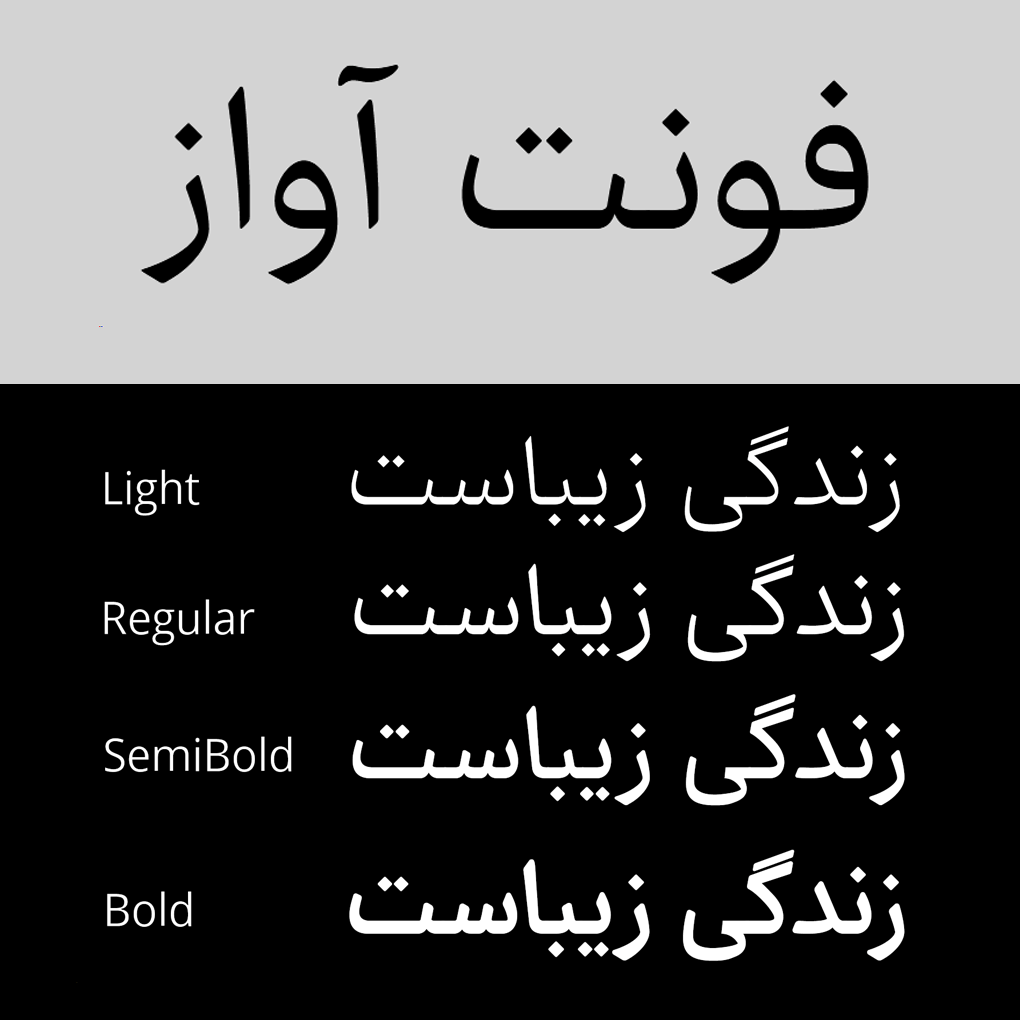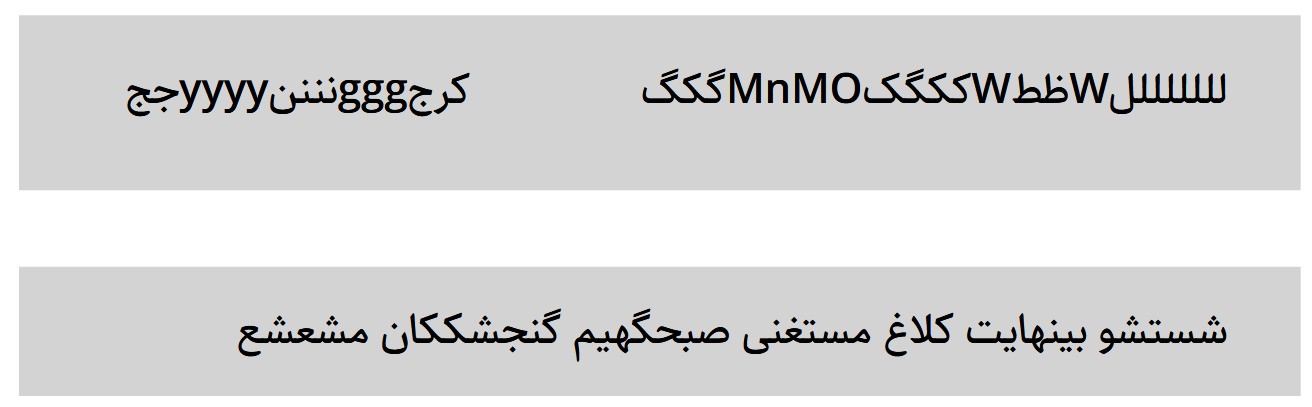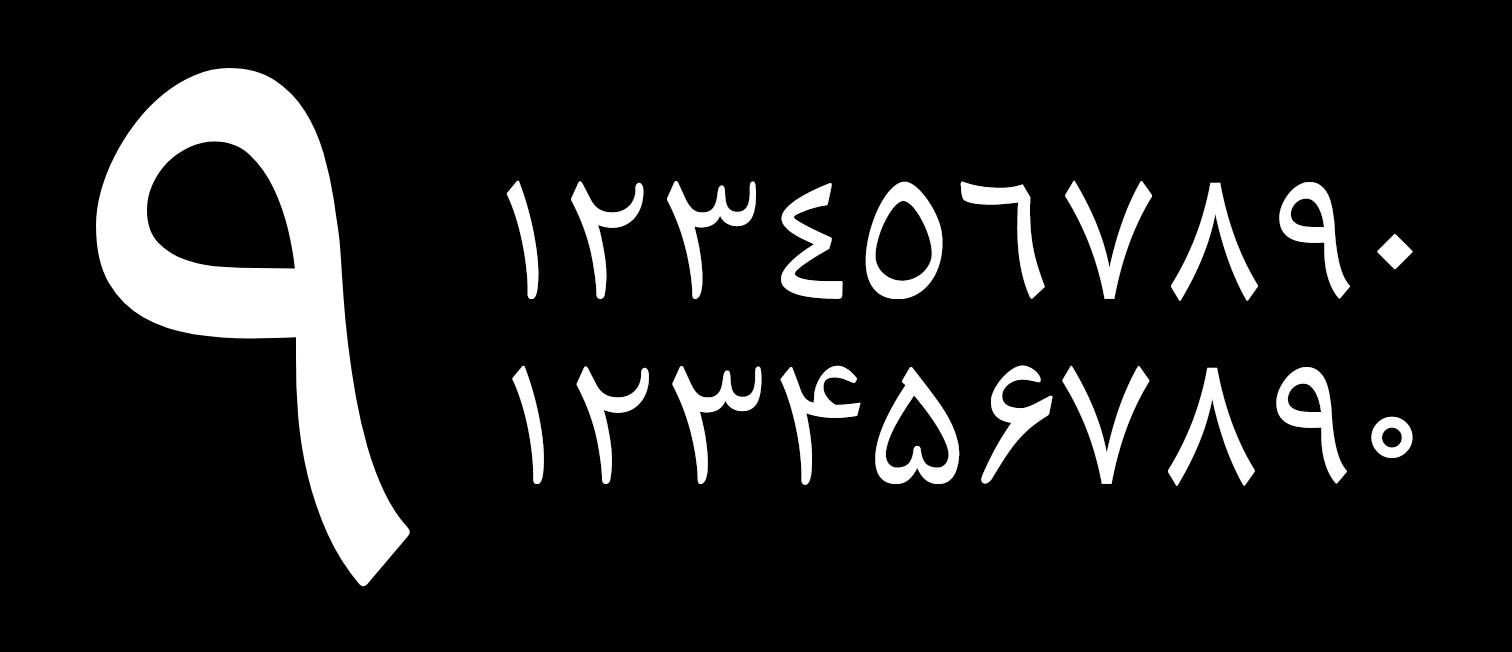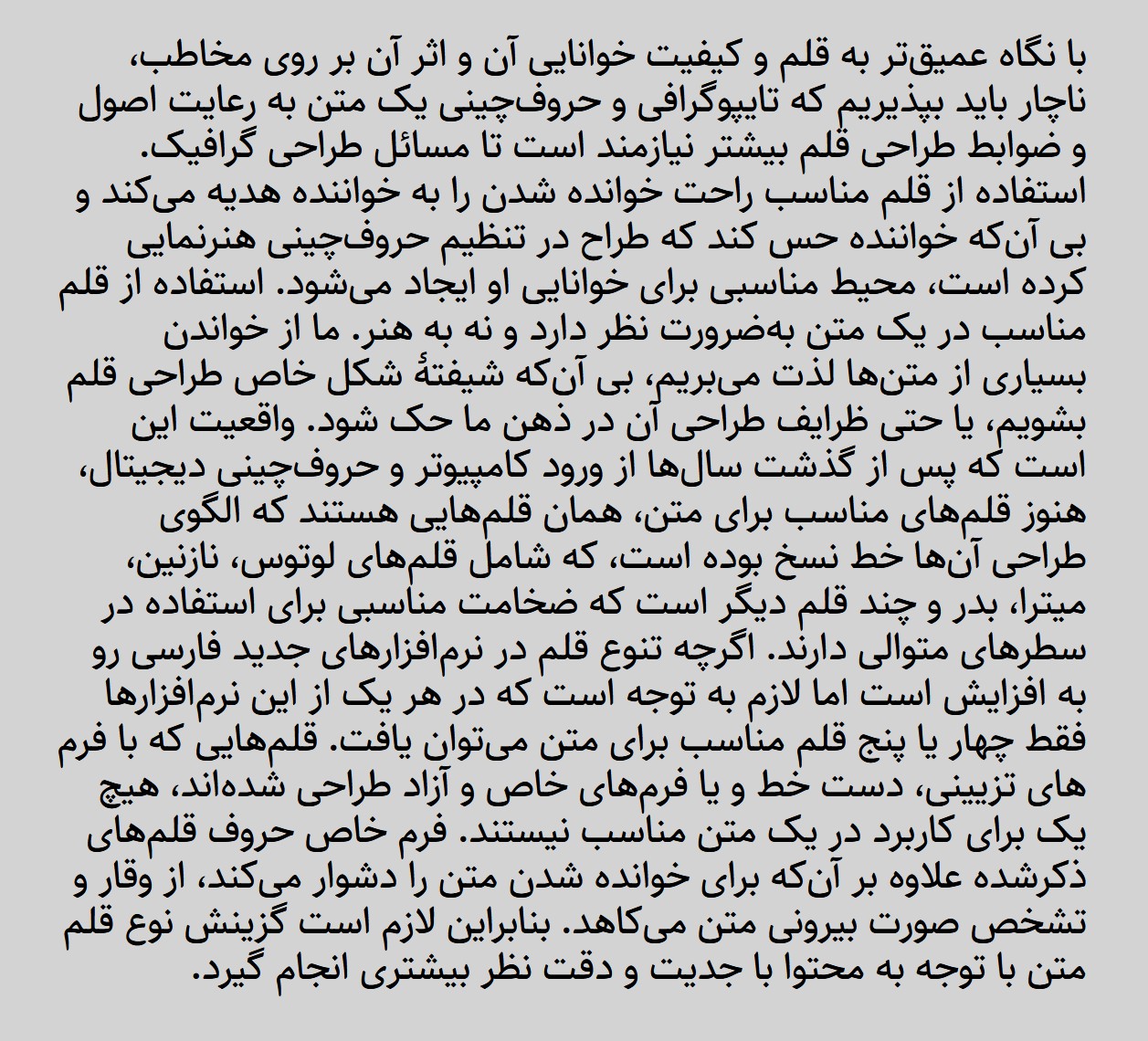
فونت آواز؛ نسل جدید فونت نسخ برای طراحان حرفه‌ای
اگر شما هم سال‌ها با فونت‌هایی مثل زر یا نازنین کار کرده باشید، احتمالاً با مشکلاتی مثل کرنینگ ضعیف، فاصله‌گذاری نامناسب بین حروف و محدودیت در استفاده در محیط وب روبه‌رو شده‌اید. این فونت‌ها اگرچه ریشه در طراحی فارسی دارند، اما دیگر پاسخگوی نیازهای امروز طراحان نیستند.
اینجا بود که فونت آواز به‌عنوان یک فونت فارسی مدرن بر پایه‌ی خط نسخ طراحی شد. فونتی که نه‌تنها اصالت خوشنویسی را حفظ کرده، بلکه تمام ایرادات نسل قبل را برطرف کرده و با استانداردهای جهانی طراحی فونت هماهنگ است.
ویژگی‌های کلیدی فونت آواز
فونت آواز دقیقاً برای کسانی ساخته شده که به‌دنبال کیفیت بالا، خوانایی بی‌نقص و ظاهر حرفه‌ای هستند. برخی از مهم‌ترین ویژگی‌های این فونت عبارت‌اند از:
• الهام از خط نسخ با رویکرد مدرن: ترکیب اصالت خوشنویسی با دقت هندسی.